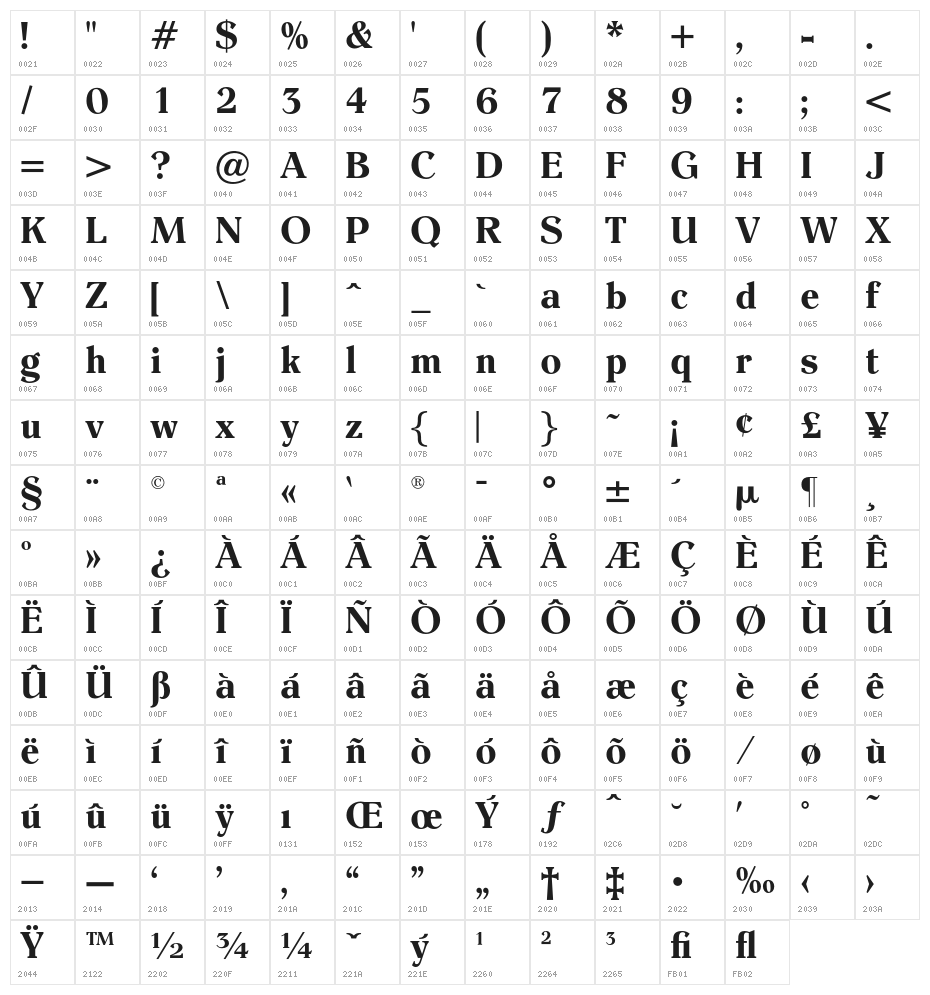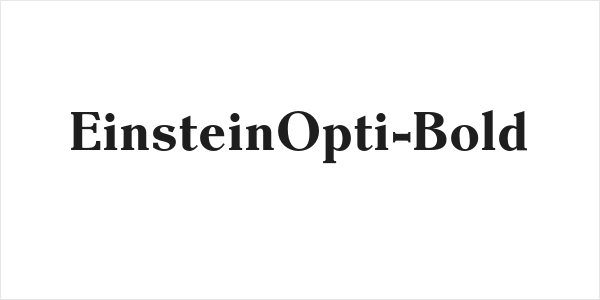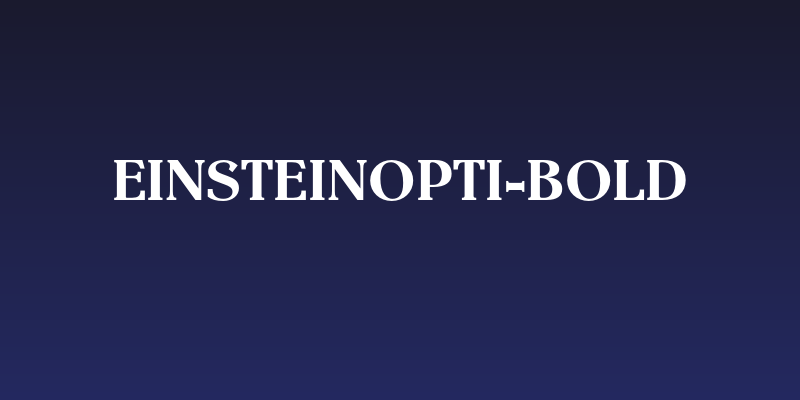
EinsteinOpti-Bold Font
| Caso d'uso | Headlines, Logos, Editorial design |
| Progetti proposti | Ideal for headlines, book covers, branding, and editorial design where a strong, traditional presence is desired. |